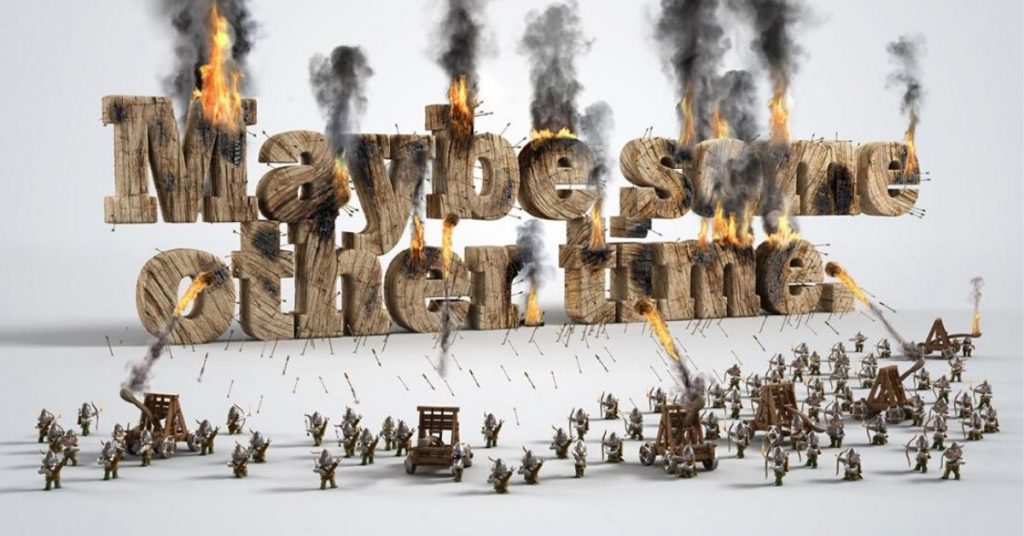
20 publicités créatives qui s'amusent avec les typographies
“La typo est un art difficile. Ça demande trop de temps. Il faut être un peu cinglé pour faire ce métier. J’ai délaissé femmes et enfants. Quand on est lié à son art, c’est comme un sacerdoce. Comme un curé. La typo c’était ma religion”.  Albert Botton — typographe
C’est à partir de cette citation que nous souhaitons aujourd’hui vous proposer une dose d’inspiration singulière. A travers ces 20 campagnes brillantes, vous pourrez nourrir votre créativité et découvrir toutes les possibilités qu’offre la typographie. Au delà du choix des mots, leur mise en scène demeures indispensable.
Automobile, food, sport, Santé, tous les secteurs sont concernés. Découvrez notre sélection de 20 campagnes inspirantes :